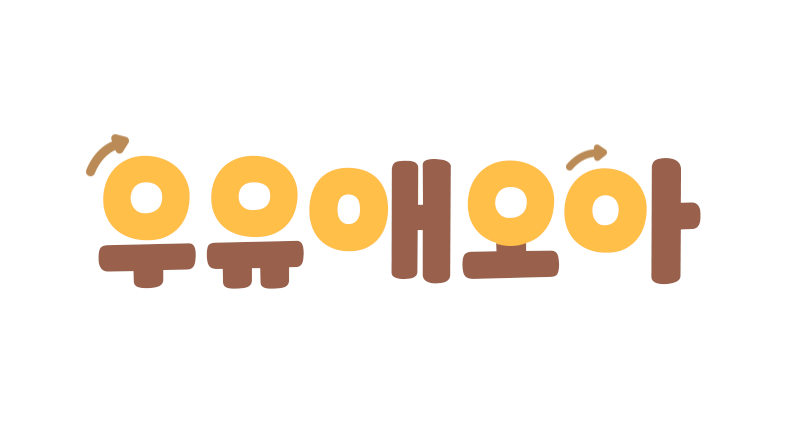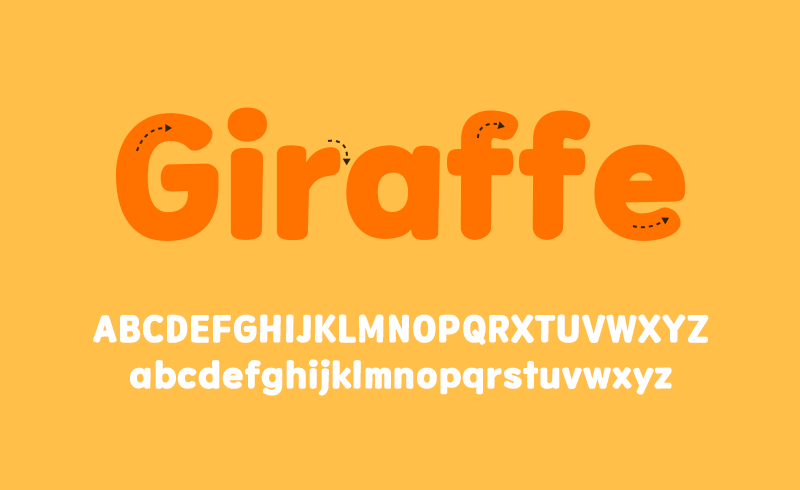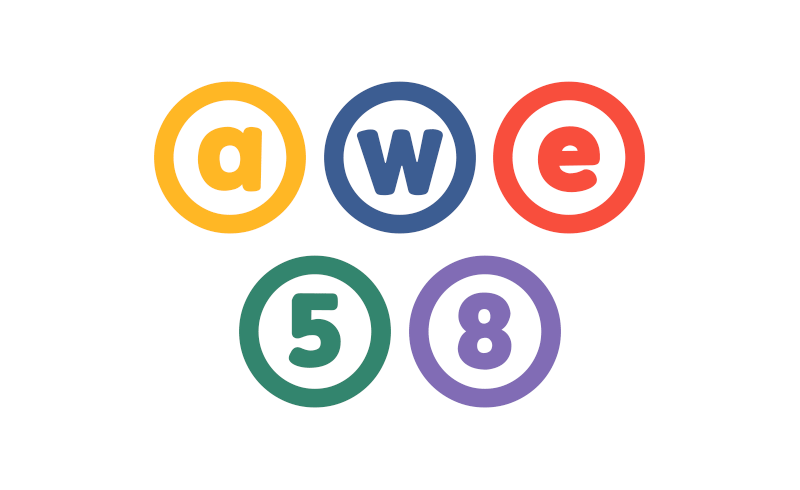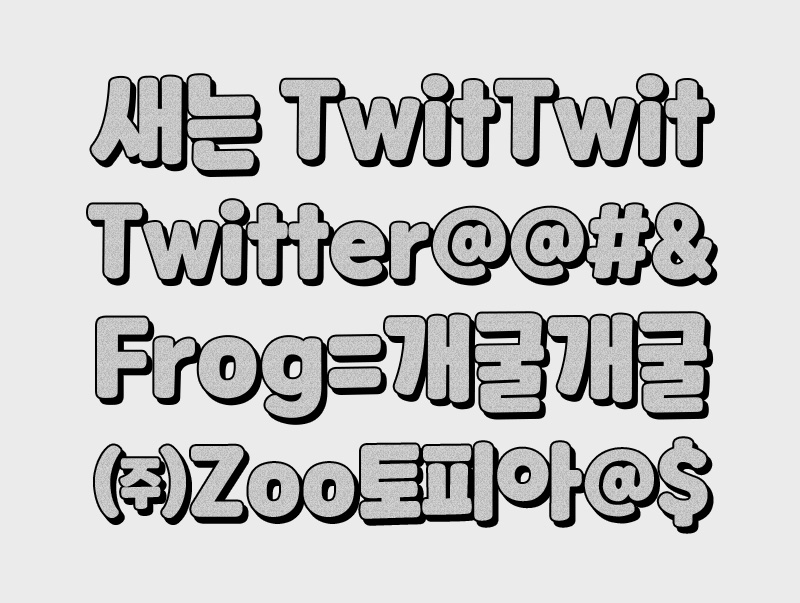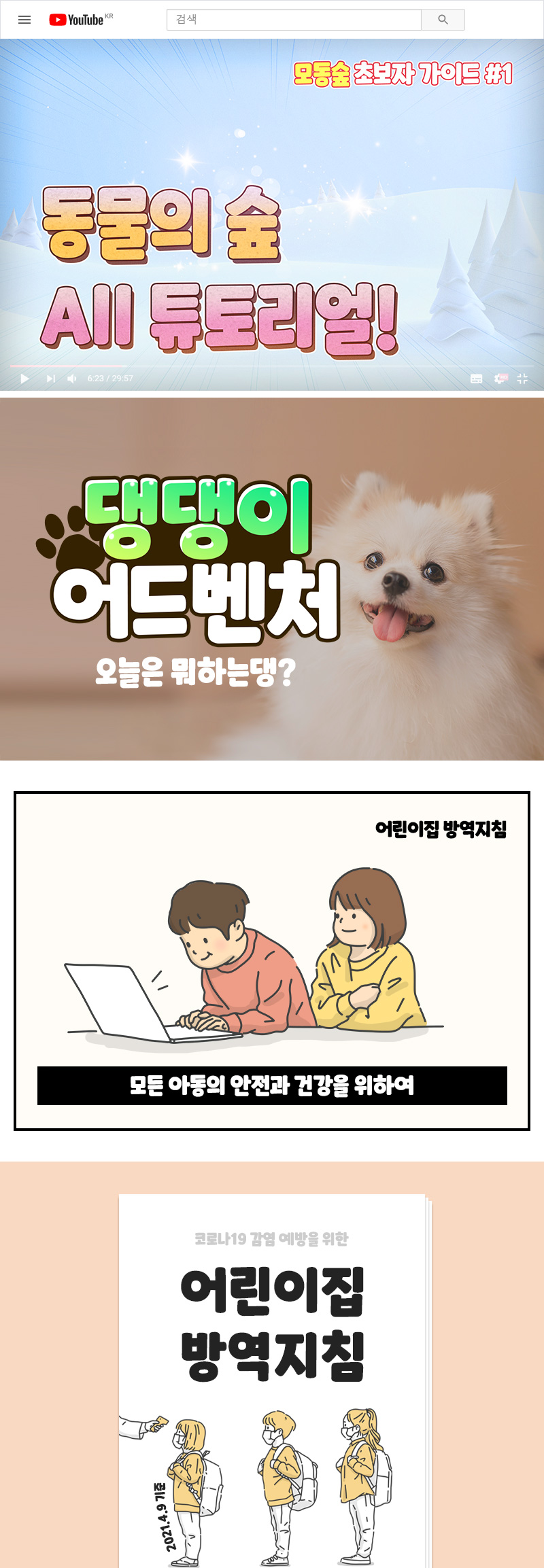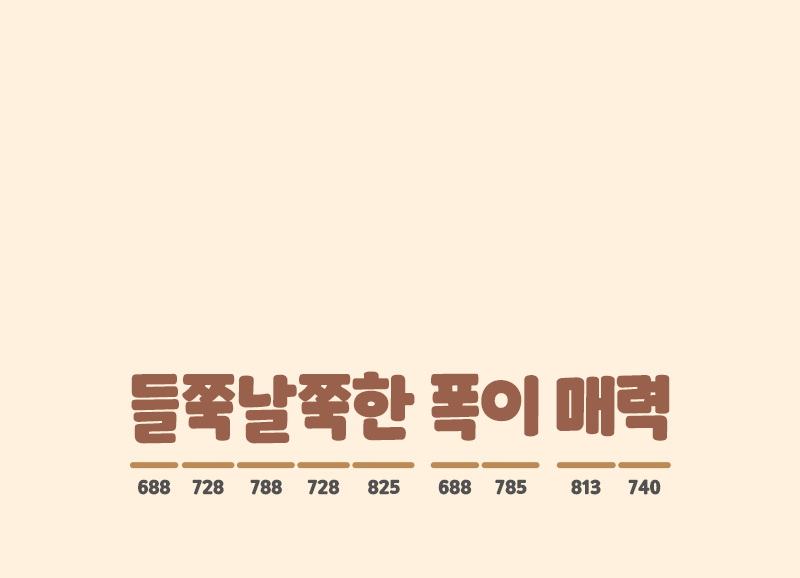
Rix애니멀
Rix애니멀은 귀여운 동물들을 연상시키는 동글동글한 인상의 손글씨 서체입니다.
두꺼운 마카로 쓴 듯 두툼한 획과 정원형의 동그란 'ㅇ'꼴이 특징입니다.
꽃처럼 피어나 별처럼 빛나는 그대에게
가변폭을 사용하여 리드미컬한 매력을 살렸습니다.
전체적으로 둥글둥글한 형태와 정원 꼴의 초성 'ㅇ'이 특징입니다.
부드럽고 귀여운 한글 컨셉과 동일하게 영문도 디자인하였습니다.
숫자/약물 디자인 또한 한글과 어우러지도록 디자인하였습니다.